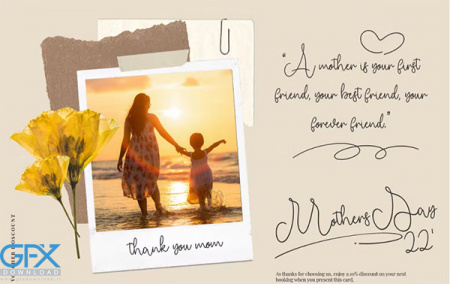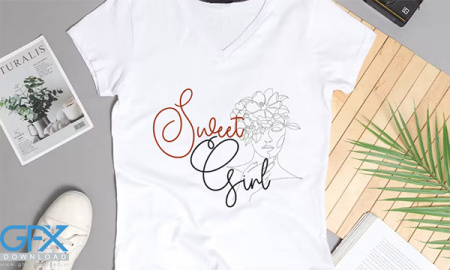
دانلود فونت رایگان انگلیسی دست نویس Jhon Caretta
دانلود فونت رایگان دست نویس Jhon Caretta
دانلود فونت رایگان انگلیسی دست نویس و خطی Jhon Caretta
یک فونت اسکریپت تک خطی است که برای نیازهای پروژه طراحی شما مناسب است، مانند؛ تم عروسی، پست های رسانه های اجتماعی، نقل قول ها، پوشش روی تصاویر، پوسترها، نیازهای چاپی، بنرهای وب سایت و موارد دیگر. دانلود فونت رایگان انگلیسی دست نویس Jhon Caretta برای برندینگ، آرم ، بسته بندی محصول ، پوستر ، دعوت نامه ، کارت تبریک ، اخبار ، وبلاگ ها و موارد دیگر مناسب است.
دانلود فونت دست نویس Jhon Caretta
فونت انگلیسی دست نویس Jhon Caretta
• مجموعه ای از حروف حروف بزرگ و کوچک
• اعداد، نماد، علائم نگارشی، و swash
• پشتیبانی چند زبانه